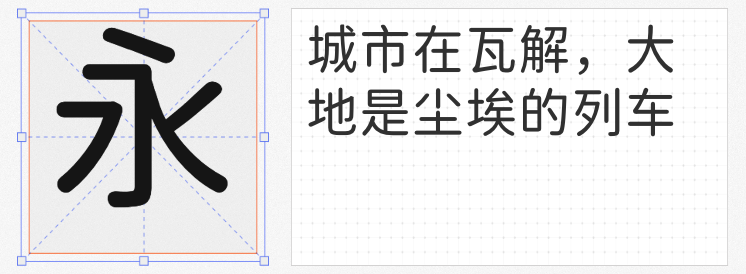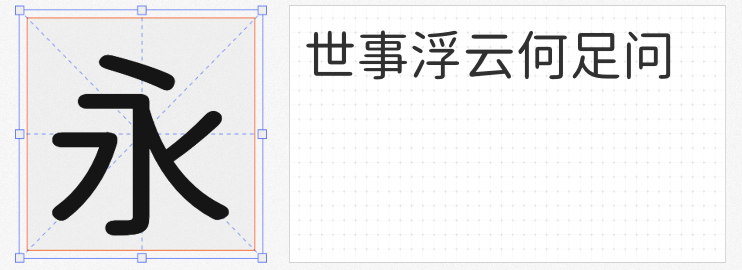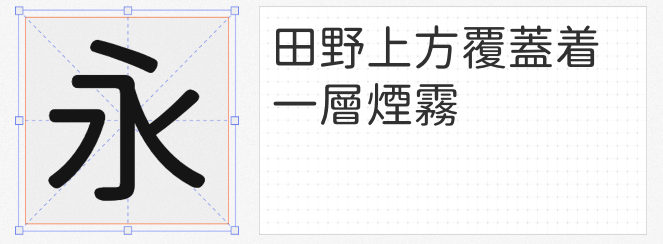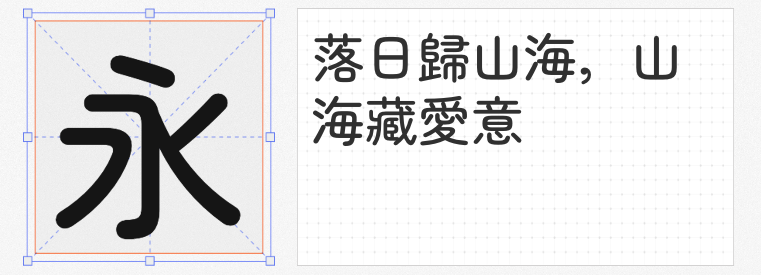
在平面设计中,圆体字体以其柔和的线条、亲切的视觉感受,成为品牌标识、UI界面、儿童读物等领域的热门选择。以下四款免费商用圆体字体,兼具实用性与艺术性,助力设计师轻松打造灵动、清新的视觉作品。
1. 未来圆 Regular
未来圆由博主基于“未来荧黑”独立圆角化改造而来,继承了未来荧黑的现代基因。相比思源黑体,其字形更收敛紧凑,中宫与字面比例优化,重心经过重新配置,版面效果简洁明快。笔画干练平直,去除了冗余装饰,却保留了圆角的柔和感,适合科技品牌、极简风海报及移动端界面设计,传递轻盈与未来感。
2. 源泉圆体TW Regular
源泉圆体以思源黑体为蓝本开发,完整保留了思源黑体的开放性与稳定性。其圆角处理自然流畅,字形中正均衡,笔画粗细适中,兼具现代感与易读性。作为一款万能字体,它适用于各类商业场景,如产品包装、宣传手册、网页正文等,既能提升设计质感,又无需担心版权风险。
3. 寒蝉圆黑体 Regular
寒蝉圆黑体基于思源黑体圆角化改造,在保留原字体简洁结构的基础上,将笔画末端处理为圆润弧度,整体风格柔和亲切。其字形略带稚拙感,适合儿童教育、母婴品牌、卡通IP等场景,也能为文艺风海报、手账模板增添一抹温暖气息。
4. 寒蝉半圆体
寒蝉半圆体以日本开源字体Zen Maru Gothic为基础调整,融合了日式设计的克制与细腻。其笔画半圆处理巧妙,既保留了黑体的力量感,又通过圆角弱化锐利感,形成独特的“柔中带刚”气质。适用于日系风格设计、文创产品、轻食品牌包装等,传递自然、治愈的视觉语言。
这四款圆体字体各具特色,或极简、或亲和、或日系清新,均支持免费商用,为设计师提供了丰富的选择空间。无论是追求现代感、童趣感还是日系美学,都能从中找到适配方案,让文字成为设计中的点睛之笔。